▼丸明オールド
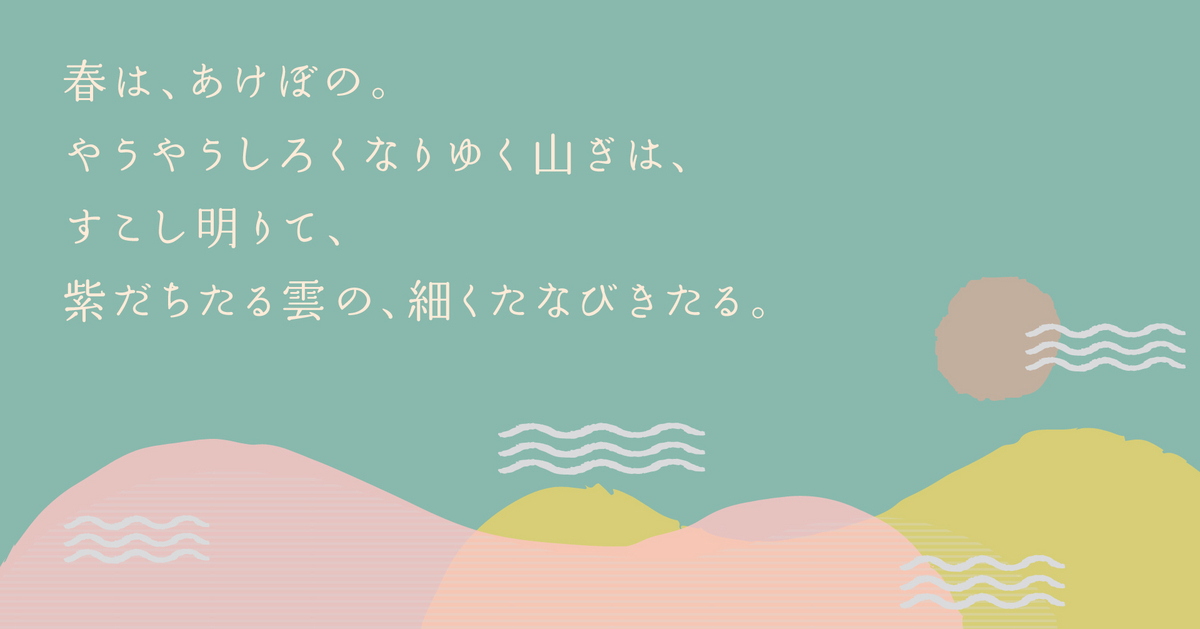
丸明朝体
2001年リリース以降、ポスターや広告、雑誌などの紙媒体から、TVCMや番組、WEBなどのデジタルコンテンツに至るまで、長く愛され使われ続けている書体。
明朝体ながらエレメントに丸を用いることで柔らかな印象を与え、筆の動きが強調された文字は躍動感がありながら、見る人に温かみや懐かしさを感じさせる。
丸明朝体には、7種類のかな違いの書体がある。
なかでもクラシカルなのにモダン、オーソドックスなのにチャーミングな丸明オールドは、多くの広告媒体や書籍などで使用されてきた。
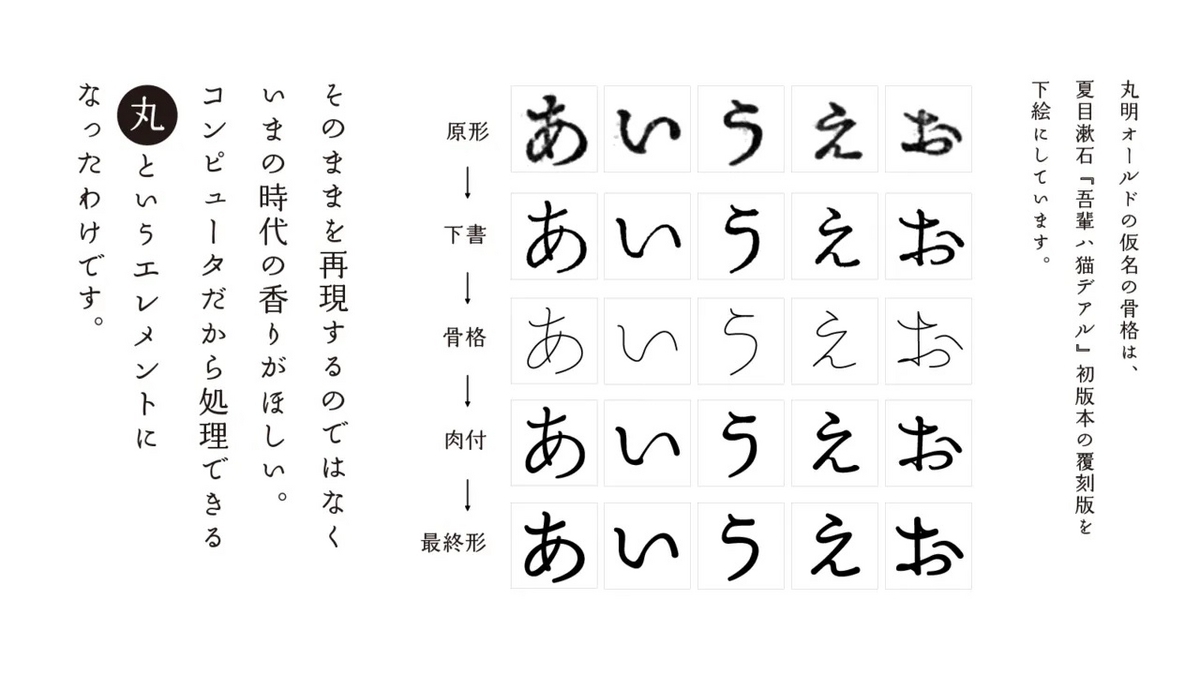
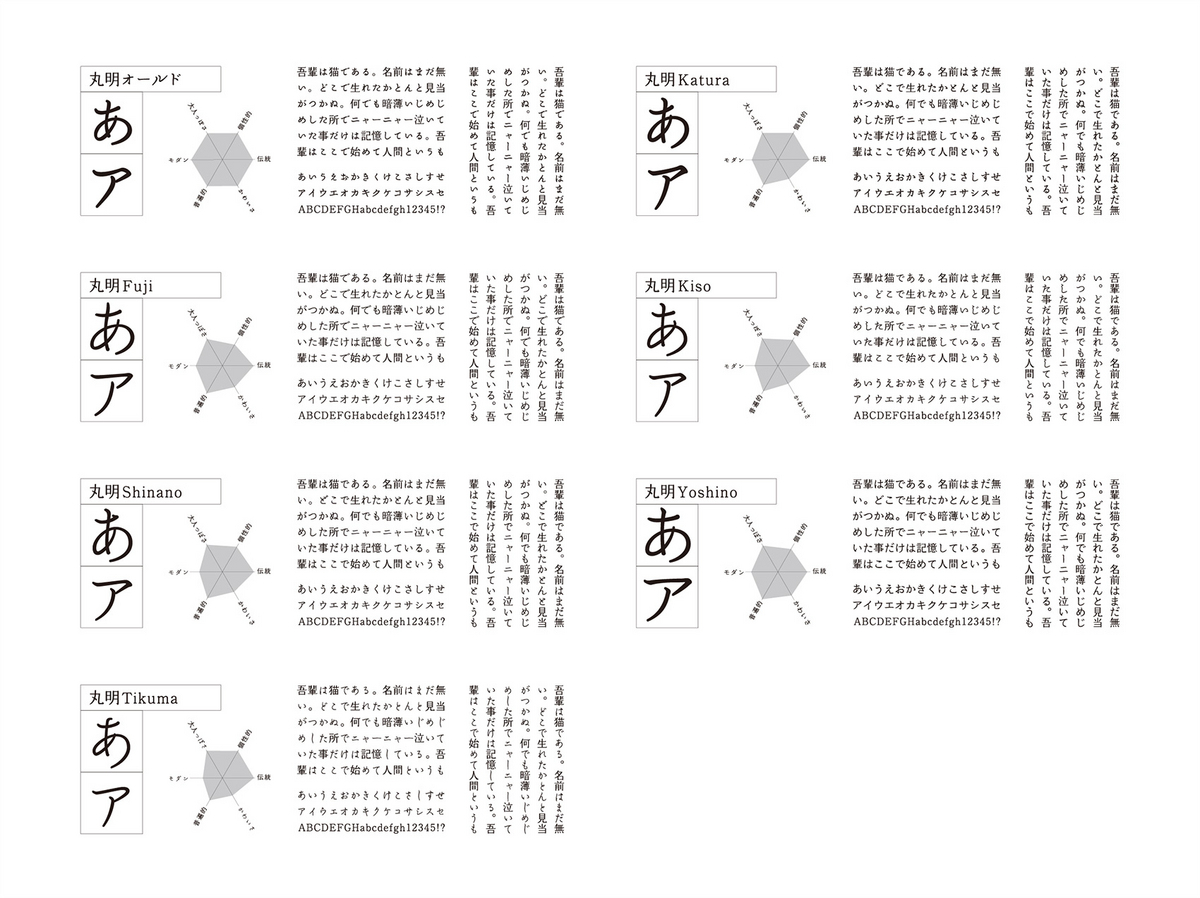
砧書体制作所
1995年設立。
ことばを伝える声には『声優』がいるのだから、ことばを伝える文字には『字優』がいてもいいよね。
そんな発想から、多くのかなのバリエーションを展開し、フォントを制作しています。
漢字と仮名のある日本語ならではのおもしろさを、砧書体制作所のフォントを通じて実感してみてください。
ことばの豊かさは、きっとこころを元気にしてくれます。